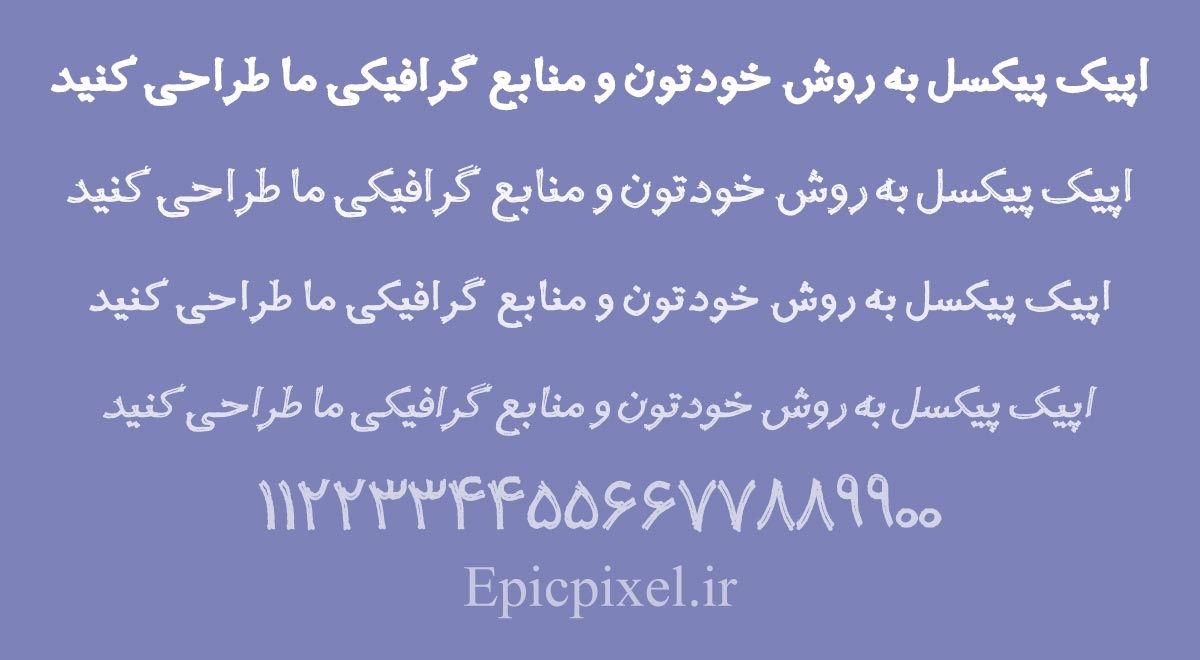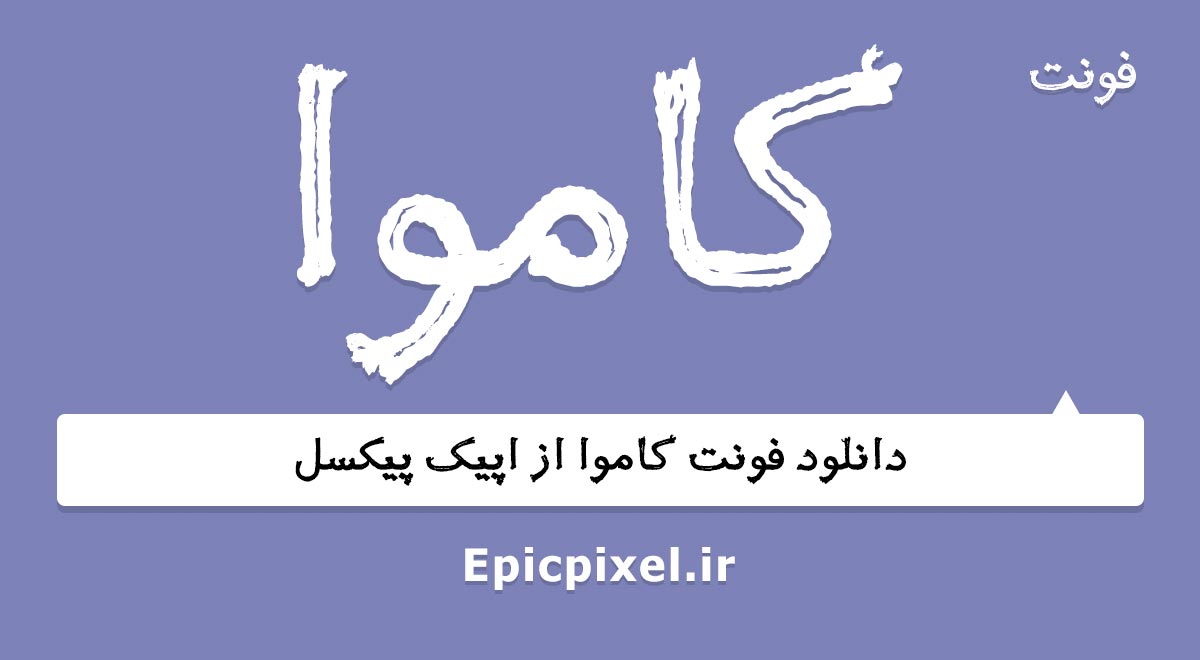
فونت کاموا فارسی
فونت کاموا یک قلم فارسی زیبا و خلاقانه
فونت کاموا یکی از جدیدترین و زیباترین قلمهای فارسی است که با ایدهای ساده ولی جذاب طراحی شده است. این فونت به شکل حروفی است که با نخ کاموا نوشته شدهاند و یک بافت طبیعی و ساده را به نمایش میگذارند. این فونت میتواند برای طرحهای گرافیکی، طراحی پوستر، لوگو، برندینگ و نمایش متنهای دوزبانه استفاده شود. در این مقاله به تاریخچه، ویژگیها، کاربردها و راهنمای دانلود و نصب فونت کاموا خواهیم پرداخت. همچنین در پایان مقاله پنج سؤال و جواب رایج در مورد این فونت را برای شما آوردهایم.
تاریخچه و طراحی فونت کاموا
نام و معنای فونت کاموا
فونت کاموا از نام گل کاموا گرفته شده است. گل کاموا گلی است خوردنی و خوشمزه که در منطقه خلخال در استان اردبیل رشد میکند. این گل به دلیل شکل زیبا و رنگهای مختلفش مورد توجه بسیاری از علاقهمندان به گل و گیاه است. همچنین از نخ این گل برای بافت قالیچه، جوراب، لباس و دستباف هم استفاده میشود. نخ کاموا نخی است نرم، لطیف، با دوام و رنگین که باعث شده است فونت کاموا هم دارای این خصوصیات باشد.
دانشجو و استاد راهنمای طراح فونت
فونت کاموا توسط خانم عطیه کامجو به عنوان یک پروژه دانشجویی در سال 1396 طراحی شده است. خانم کامجو دانشجوی رشته گرافیک و هنرهای کاربردی در دانشگاه هنر اصفهان بودهاند. این پروژه تحت نظر آقای مسلم ابراهیمی، استاد گرافیک و طراحی حروف در همان دانشگاه انجام شده است. آقای ابراهیمی یکی از معروفترین و موفقترین طراحان قلم فارسی هستند که تا کنون بیش از 50 فونت مختلف را طراحی کردهاند. برخی از معروفترین فونتهای ایشان عبارتند از: فونت نسخ، فونت نستعلیق، فونت تحریر، فونت ساحل، فونت تندیس و فونت مسلم.
فونت کاموا با روش و ابزار سادهای طراحی شده است. خانم کامجو با استفاده از نخ کاموا حروف الفبای فارسی را روی یک بستر سفید نوشته و سپس با دوربین عکاسی از آنها عکس گرفتهاند. سپس با استفاده از نرمافزار Adobe Photoshop عکسها را ویرایش و به صورت دیجیتال درآوردهاند. در نهایت با استفاده از نرمافزار FontLab Studio حروف را به قلم تبدیل کرده و تنظیمات لازم را بر روی آنها اعمال کردهاند.
نسخهها و بروزرسانیهای فونت
فونت کاموا در حال حاضر دارای 1 وزن رایگان است که شامل حروف فارسی، عدد، علائم نگارشی و حروف انگلیسی مشابه است. این فونت در سال 1396 به صورت رایگان منتشر شده و در سال 1401 نسخه 1.1 آن با برخی بهبودها و رفع ایرادات منتشر شده است. خانم کامجو قصد دارند در آینده نزدیک نسخههای جدیدتر و با وزنهای مختلف از این فونت را منتشر کنند.
ویژگیها و خصوصیات فونت کاموا
نحوه نمایش حروف فارسی و انگلیسی
فونت کاموا یک فونت دوزبانه است که هم حروف فارسی و هم حروف انگلیسی
فونت کاموا یک فونت کامل و جامع است که پشتیبانی از حروف و علائم خاص را دارد. این فونت شامل حروف فارسی، عرب، کردی، اردو، پشتو، ترکی و … است. همچنین این فونت شامل علائم رسم الخط مانند سجده، تشدید، همزه، مد، تنوین و … است. این فونت همچنین شامل علائم نگارشی مانند نقطه، ویرگول، نقطهویرگول، دونقطه، علامت سؤال، علامت تعجب، پرانتز، کروشه، آکولاد و … است. این فونت همچنین شامل عددهای فارسی و عرب است که با شکل نخ کاموا طراحی شدهاند.
کاربردها و استفادههای فونت کاموا
طرحهای گرافیکی و طراحی پوستر
فونت کاموا یک فونت مناسب برای طرحهای گرافیکی و طراحی پوستر است. این فونت با ظاهر زیبا و خلاقانه خود میتواند برای ایجاد تاثیر بصری و جذب توجه مخاطب مفید باشد. این فونت میتواند برای نمایش متنهای تبلیغاتی، سخنرانی، شعار، دعوتنامه، اطلاعرسانی و … استفاده شود. این فونت با ترکیب با رنگها، تصاویر، شکلها و سایر عناصر گرافیکی میتواند طرحهای جذاب و خلاقانه ایجاد کند.
فونت کاموا یک فونت مناسب برای نشرات و مجلات هنری است. این فونت با ظاهر طبیعی و ساده خود میتواند برای نمایش متنهای هنری، ادبی، شعر، داستان، نقد و بررسی و … استفاده شود. این فونت با ایجاد یک حس گرم، صمیمی، دوستانه و خلاق در خواننده میتواند برای انتقال پیامها و احساسات هنرمند موثر باشد. این فونت با ترکیب با سبکها، روشها و جنبههای مختلف هنری میتواند نشرات و مجلات هنری را زیبا و جذاب کند.
لوگو و برندینگ
فونت کاموا یک فونت مناسب برای لوگو و برندینگ است. این فونت با ظاهر زیبا و خلاقانه خود میتواند برای ایجاد هویت، شناسایی، تمایز و اعتبار برای یک برند، شرکت، سازمان، محصول، خدمات و … استفاده شود. این فونت با ابراز فرهنگ، سلیقه و خلاقیت طراح میتواند برای جذب مخاطبان و مشتریان هدف مفید باشد. این فونت با ترکیب با علائم، نمادها، رنگها و سایر عناصر بصری میتواند لوگو و برندهای منحصر به فرد و حرفهای ایجاد کند.
نمایش متنهای دوزبانه
فونت کاموا یک فونت دوزبانه است که هم حروف فارسی و هم حروف انگلیسی را پشتیبانی میکند. این فونت با ظاهر یکسان و هماهنگ حروف فارسی و انگلیسی میتواند برای نمایش متنهای دوزبانه استفاده شود. این فونت با ایجاد یک تعادل بین زبانها میتواند برای انتقال پیامها و اطلاعات به مخاطبان مختلف موثر باشد. این فونت با ترکیب با سایر عناصر گرافیکی میتواند متنهای دوزبانه را زیبا و جذاب کند.